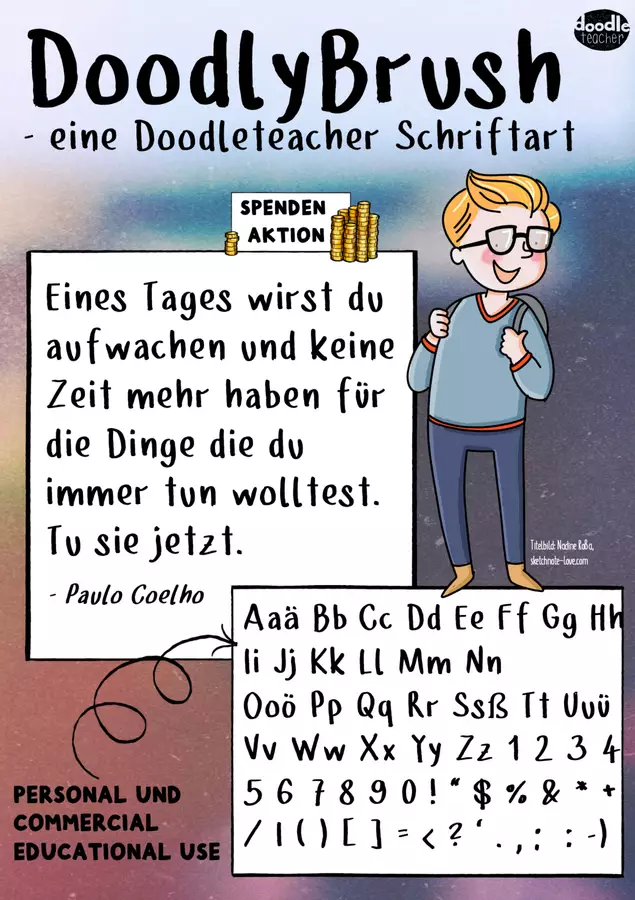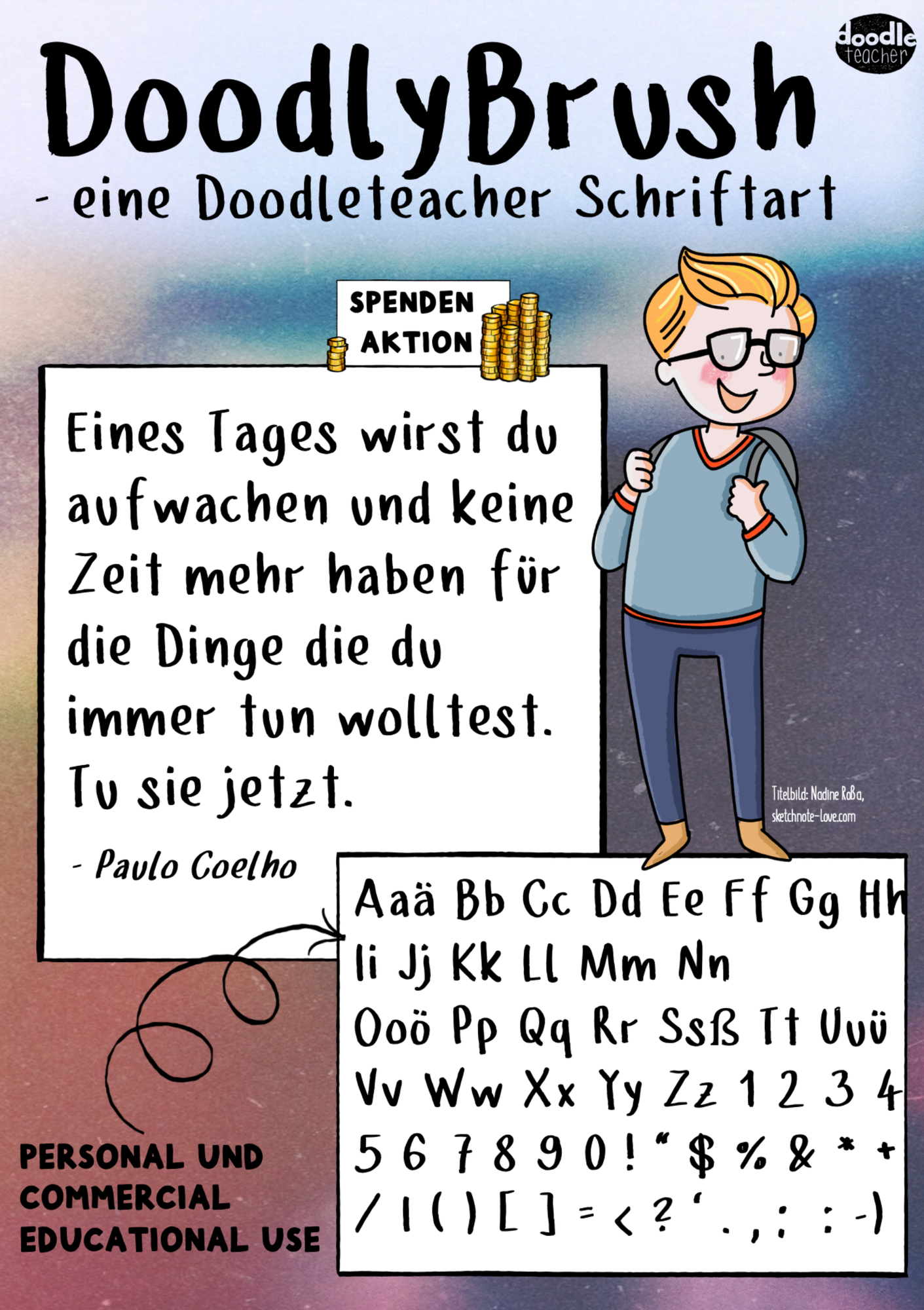
Eine sehr schöne und spielerische Schrift mit einem etwas dickeren Pinsel gezeichnet. Auch toll für Überschriften / Cover und Schriftzüge. Gibt es auch im PAKET!
Doodly Brush - Font / Schriftart